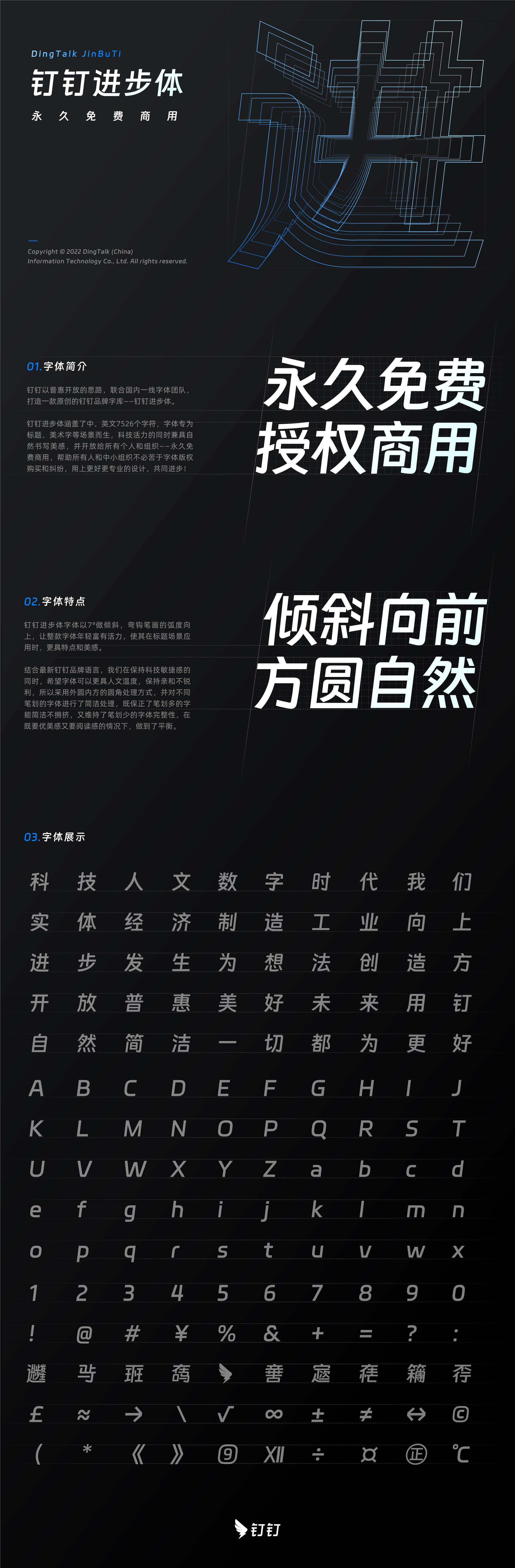
钉钉进步体
字体简介
钉钉以普惠开放的思路,联合国内一线字体团队,打造一款原创的钉钉品牌字库——钉钉进步体。 钉钉进步体涵盖了中、英文7526个字符,字体专为标题、美术字等场景而生,科技活力的同时兼具自然书写美感,并开放给所有个人和组织——永久免费商用,帮助所有人和中小组织不必苦于字体版权购买和纠纷,用上更好更专业的设计,共同进步!
字体展示